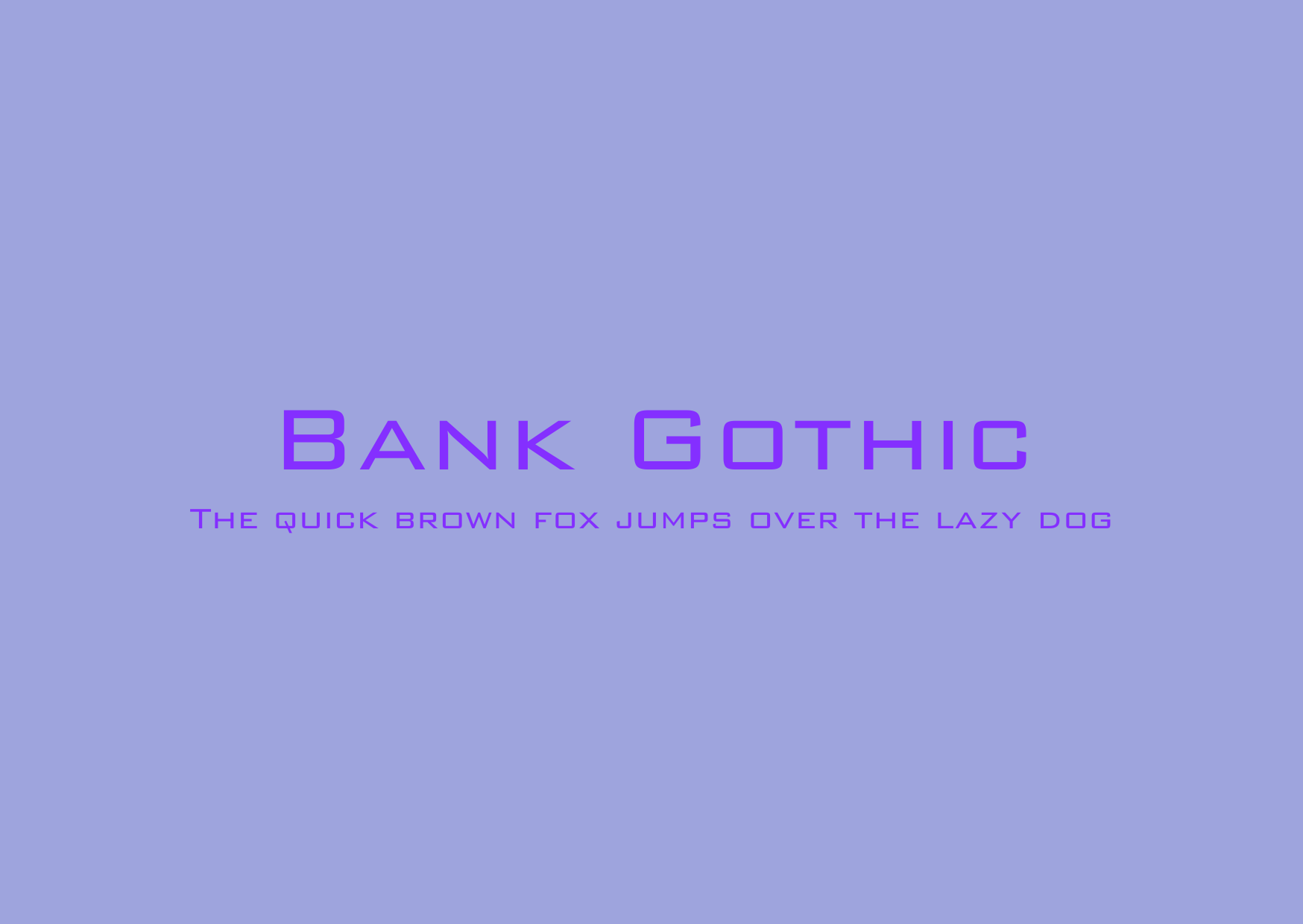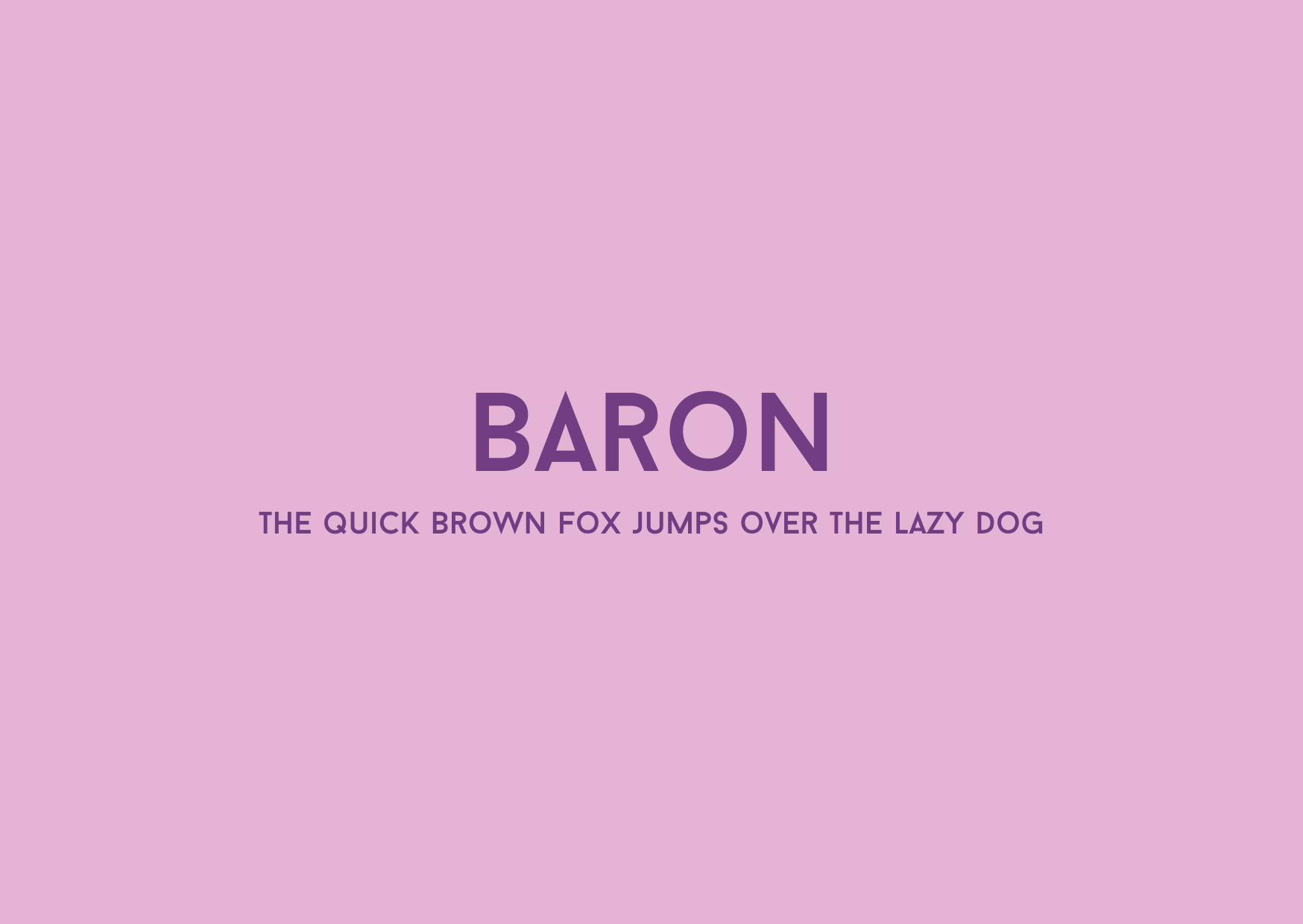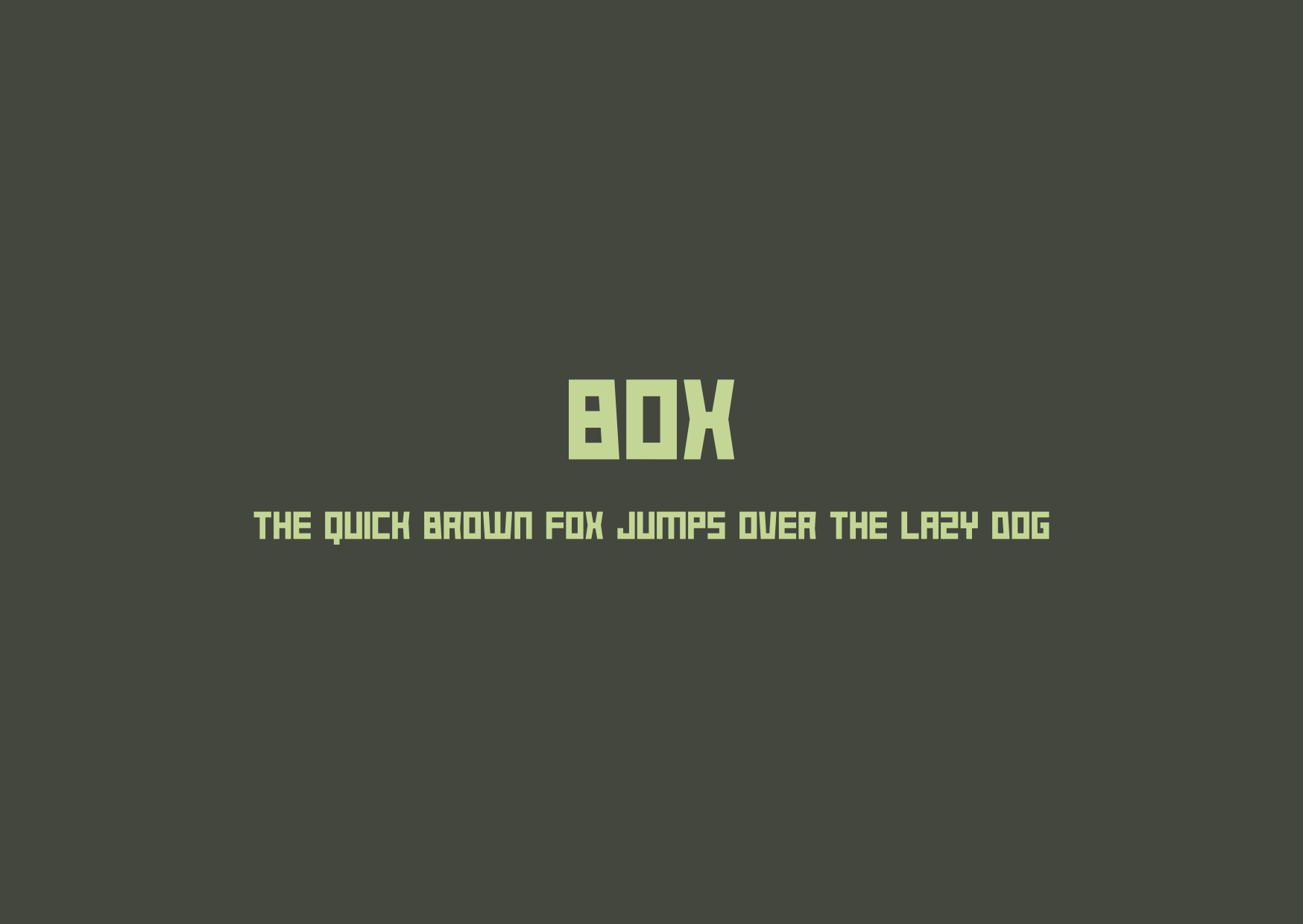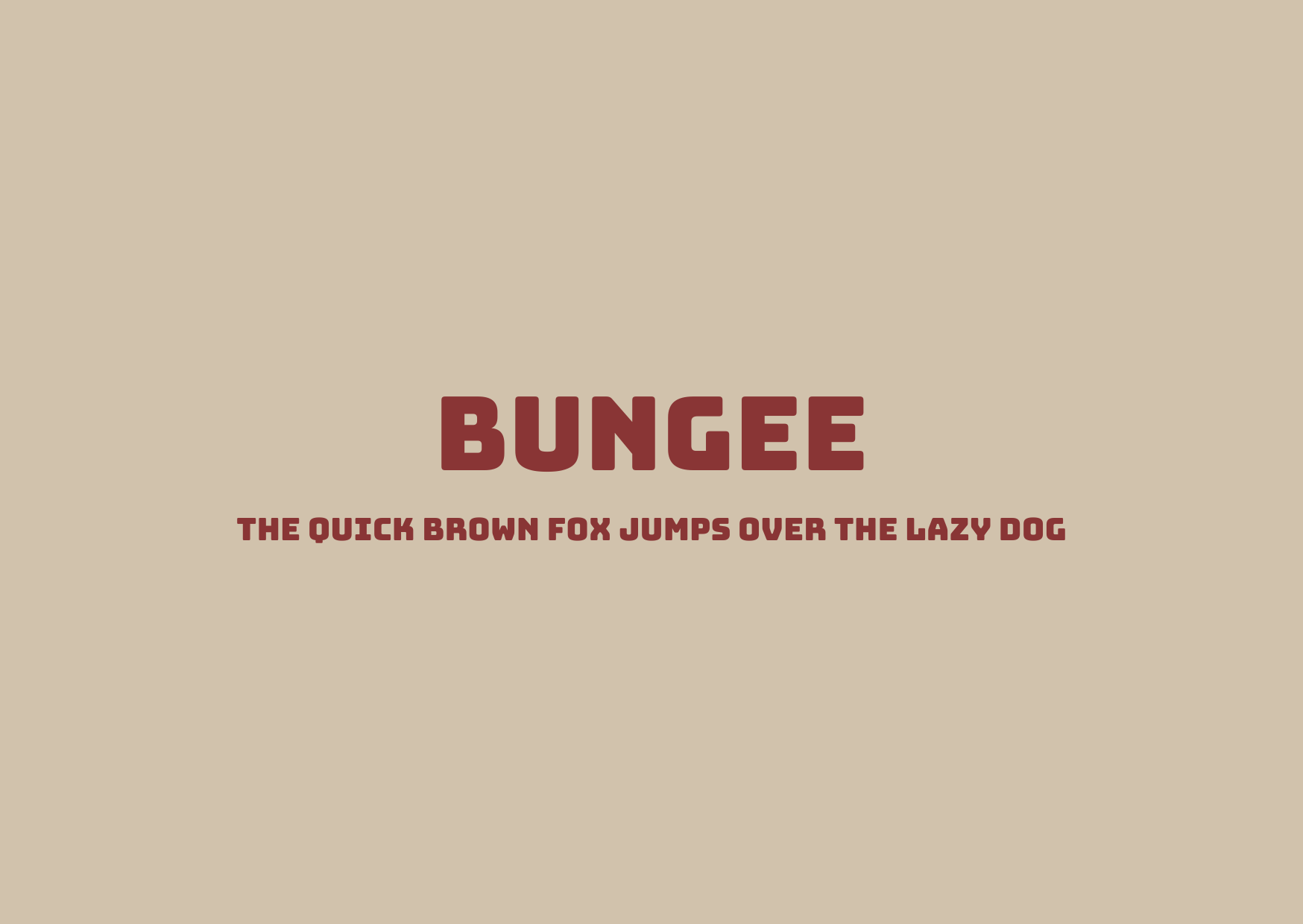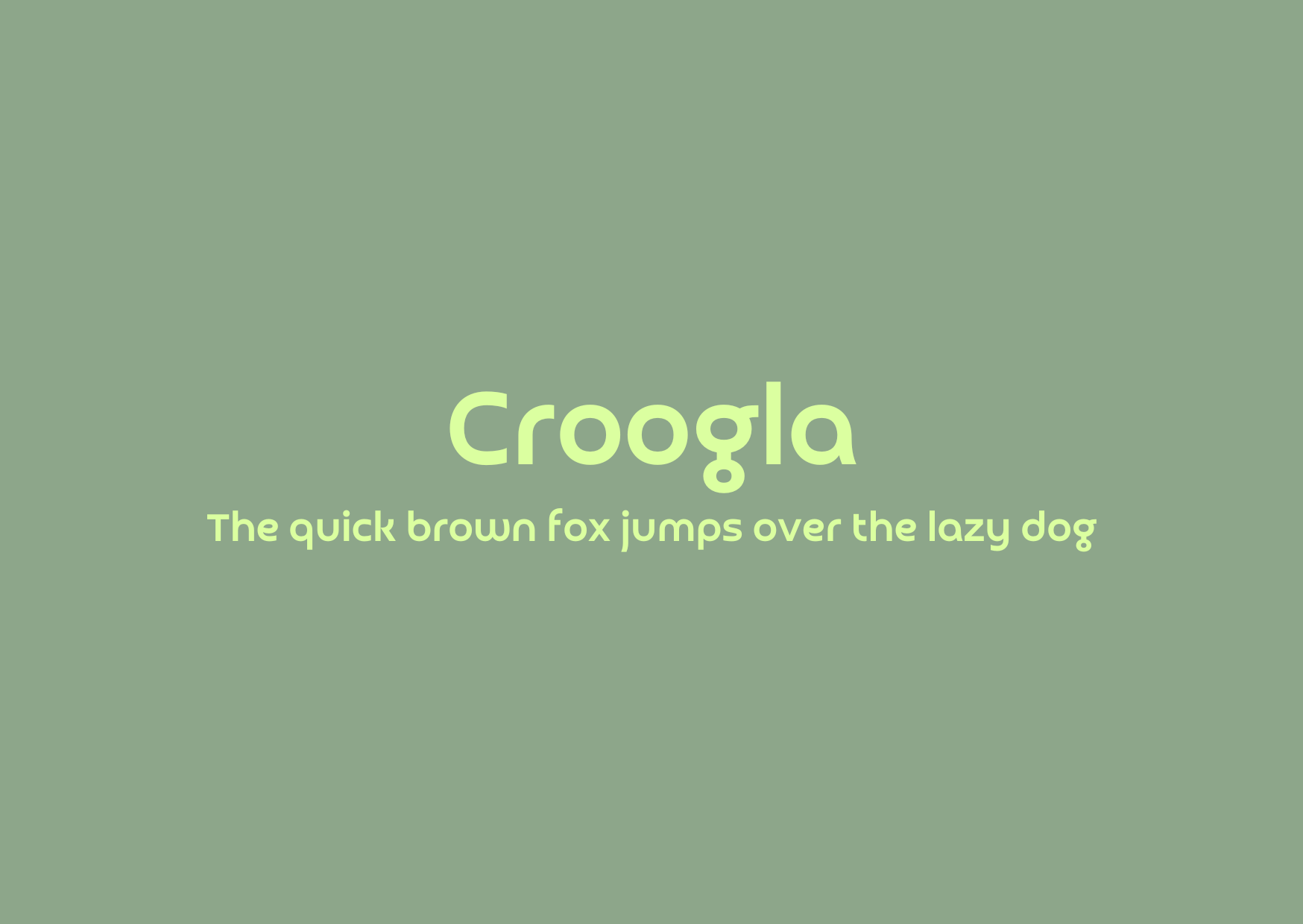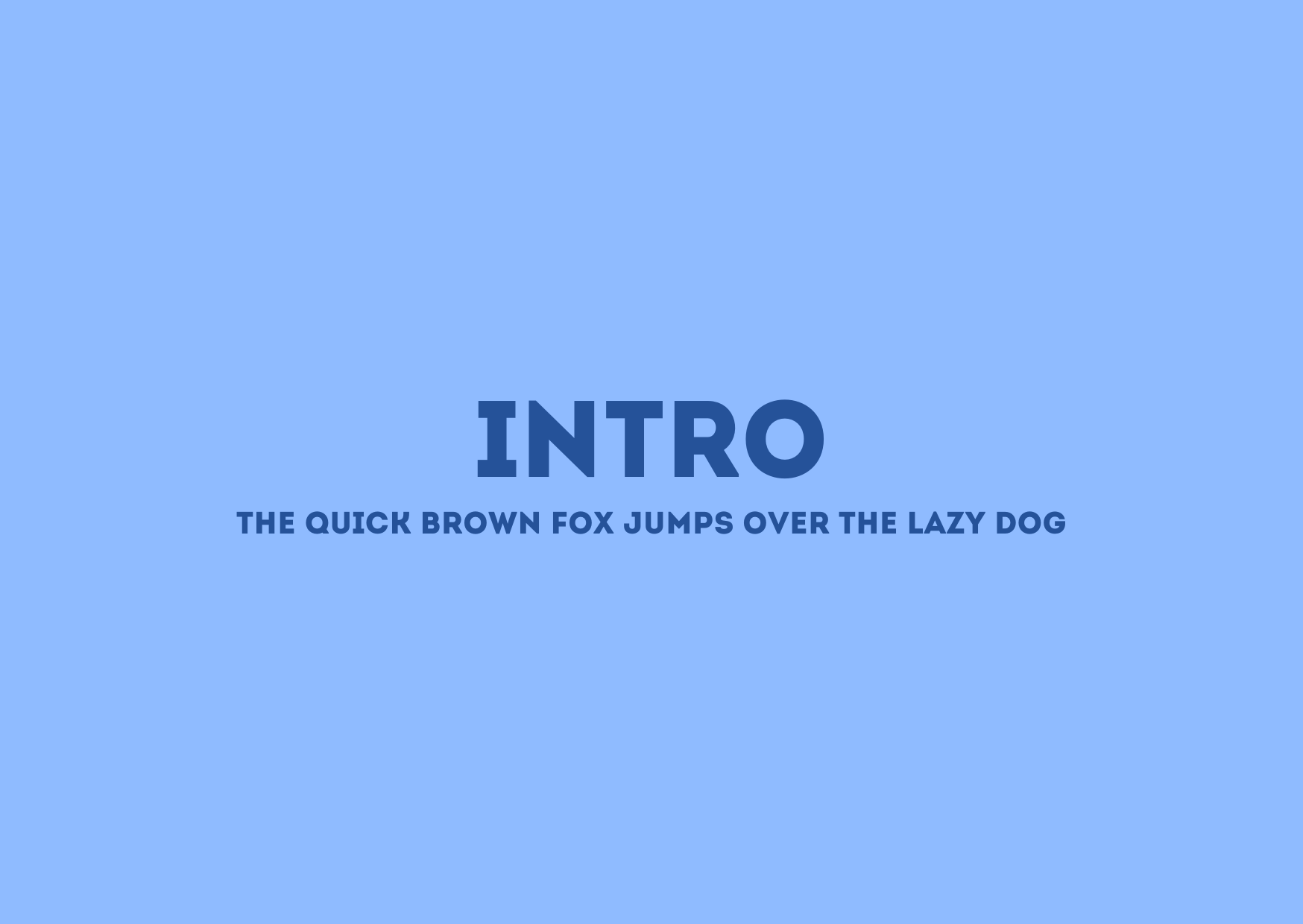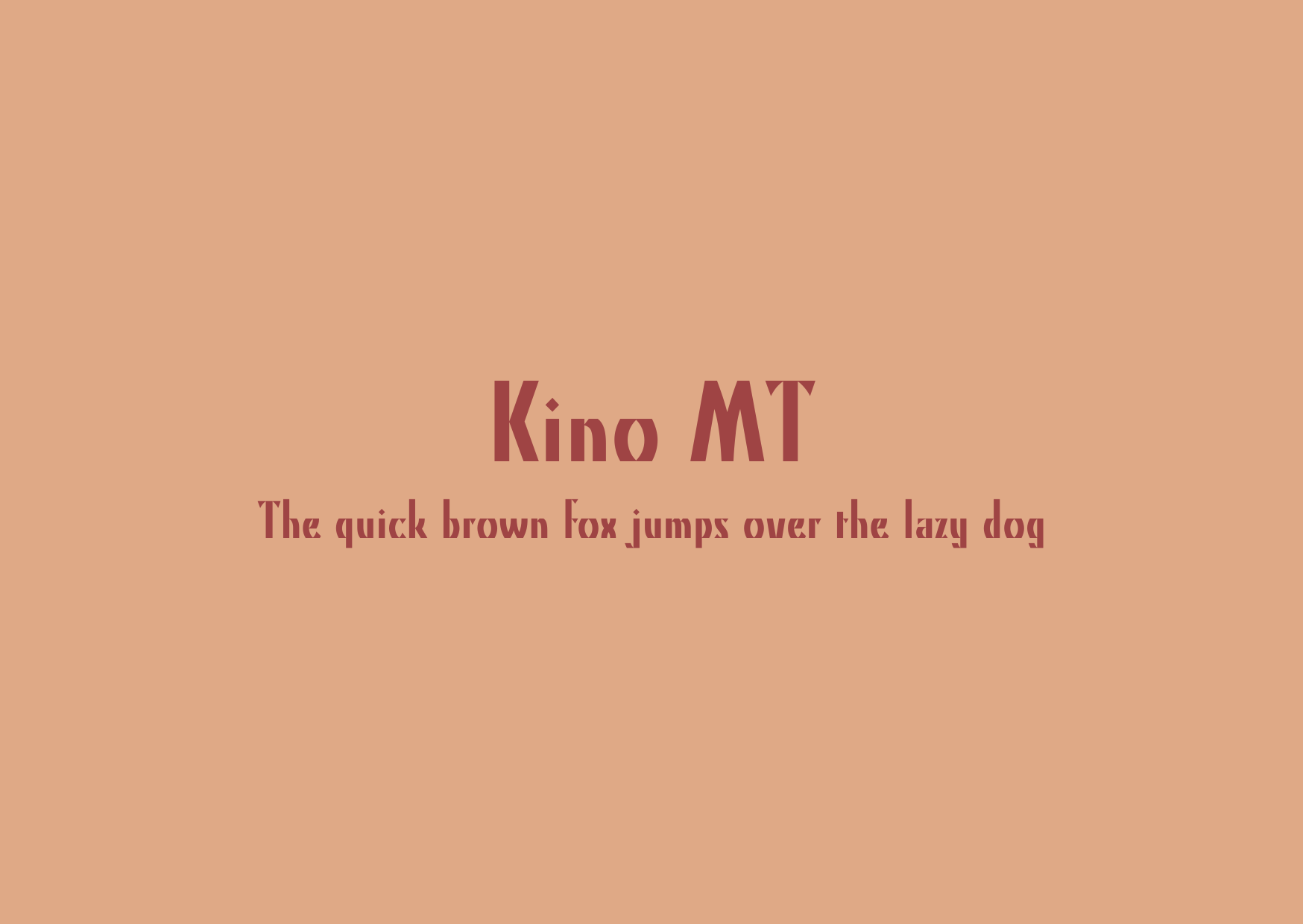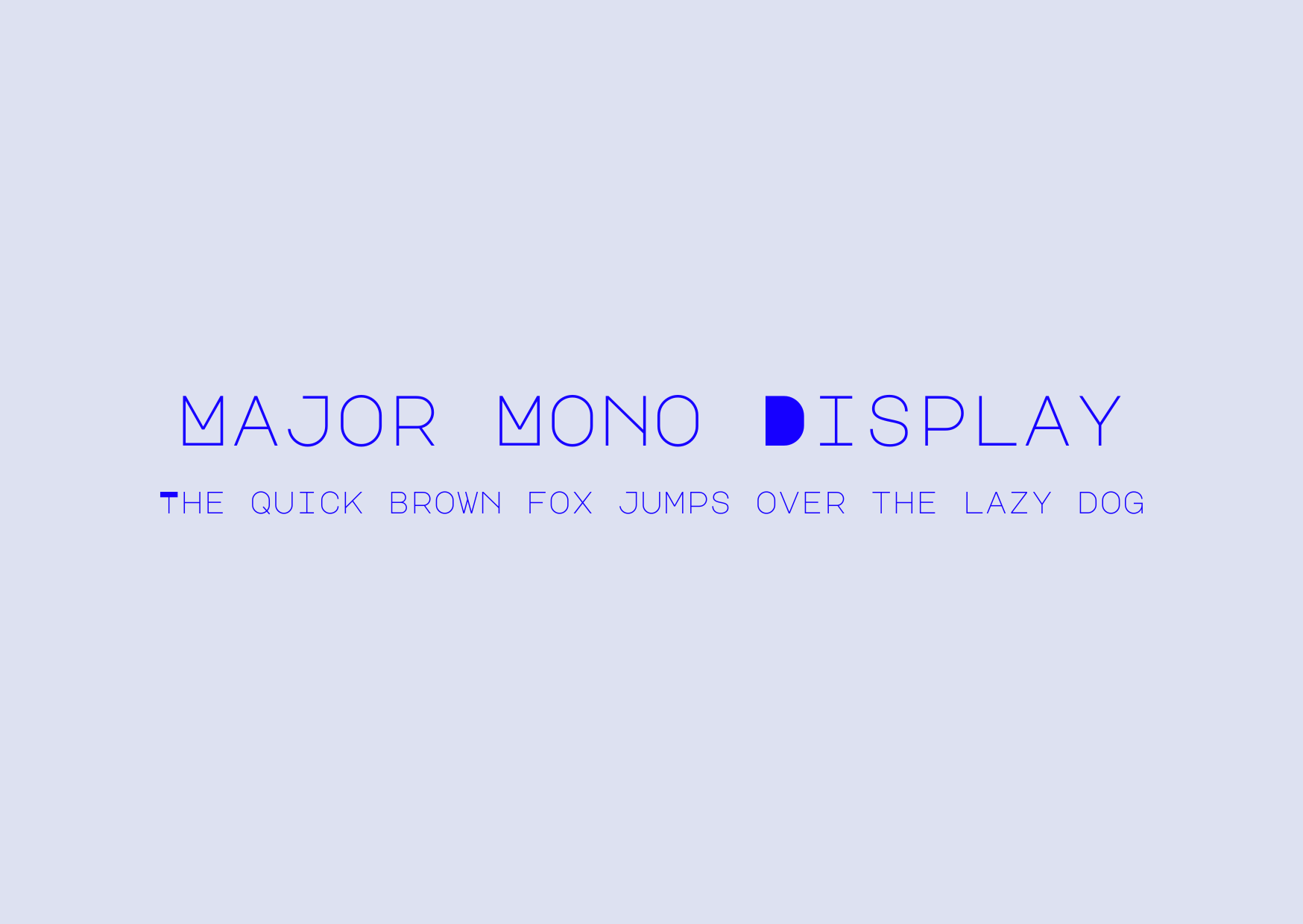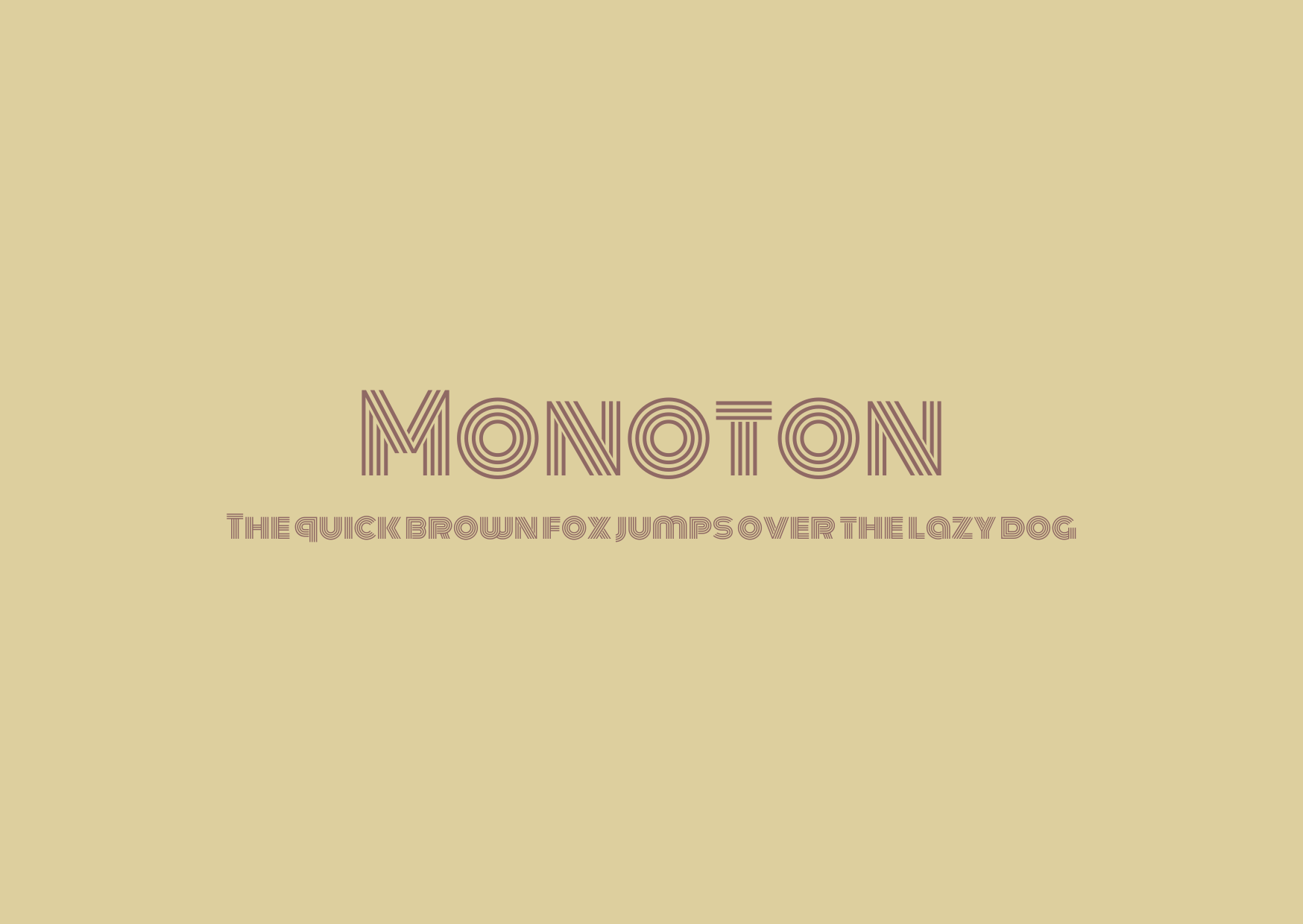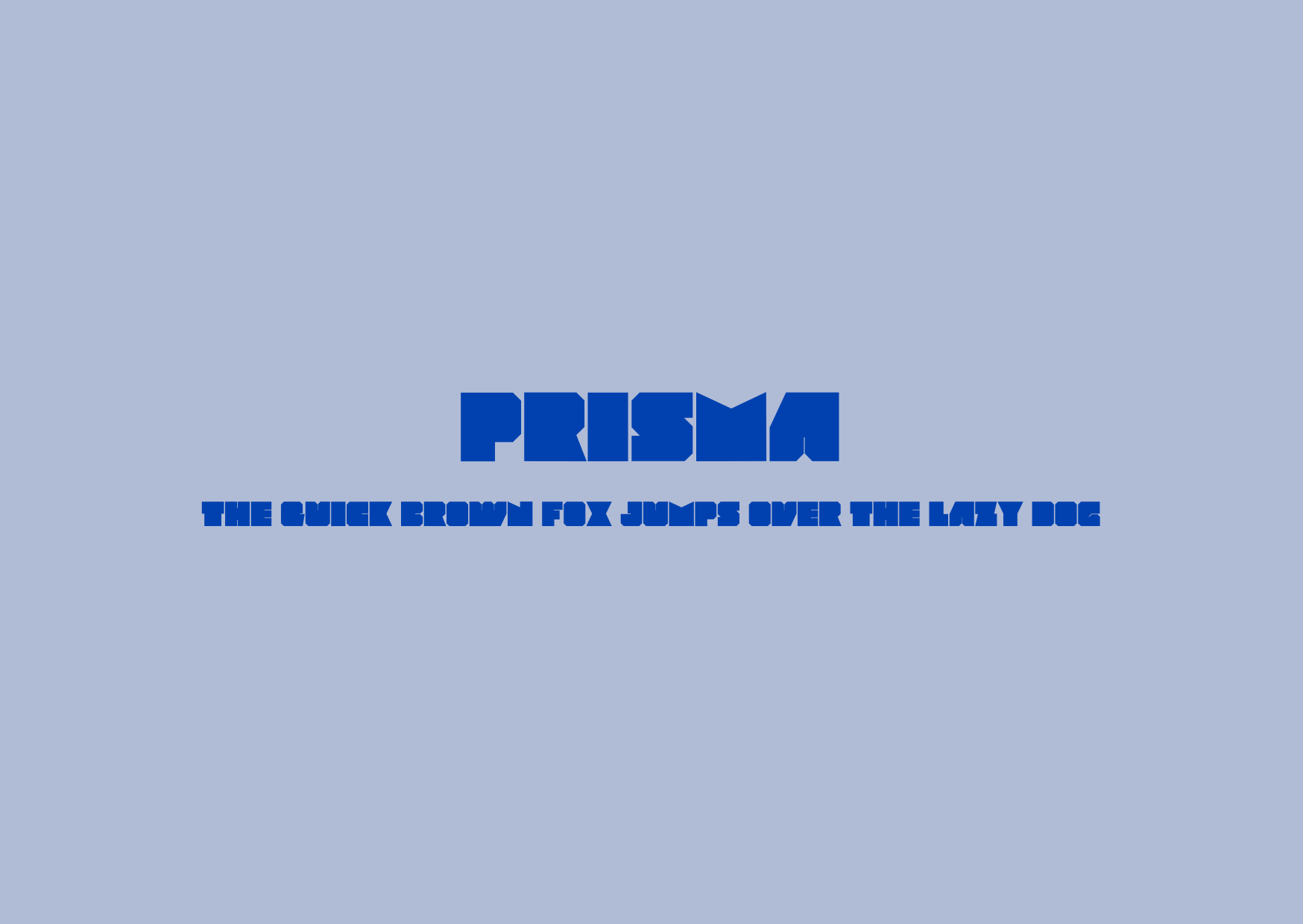
15 polices d'écritures géométriques gratuites à télécharger
Vous cherchez à donner une touche graphique et tendance à vos créations ? Découvrez sans plus attendre ces 15 polices d'écriture géométriques à télécharger gratuitement !
Du minimalisme épuré aux formes audacieuses, ces typographies originales apporteront une dimension unique à vos designs. Qu'il s'agisse d'un logo, d'une affiche, d'un site web ou d'un packaging, elles sauront mettre en valeur votre message avec style.
Les caractéristiques d'une police d'écriture géométrique
• Une police d'écriture géométrique se caractérise par un design épuré et minimaliste, mettant en avant des formes simples, des lignes droites et des angles francs.
• Les polices d'écriture géométriques se trouvent dans la classification des polices sans empattement ou display. Leur apparence neutre et modulaire est souvent basée sur des formes géométriques de base.
• Ce type de police reste lisible et clair, que ce soit pour du texte de paragraphe ou des titres, et convient donc à de nombreux usages, que ce soit sur le web ou pour l'impression.
• Elles peuvent apporter de la personnalité et de l'originalité, ce qui les rend idéales pour les projets créatifs et originaux qui souhaitent se démarquer.
Police écriture géométrique Major Mono Display
Police écriture géométrique League Spartan
Police écriture géométrique SK Primo
Police écriture géométrique Croogla
Police écriture géométrique Monoton
Police écriture géométrique Bank Gothic
Police écriture géométrique Baron
Police écriture géométrique - Box
Police écriture géométrique Intro
Police écriture géométrique Bungee
Police écriture géométrique Sifonn
Police écriture géométrique Rubik Mono
Police écriture géométrique Kino MT
Police écriture géométrique Prisma
Police écriture géométrique Peace Sans